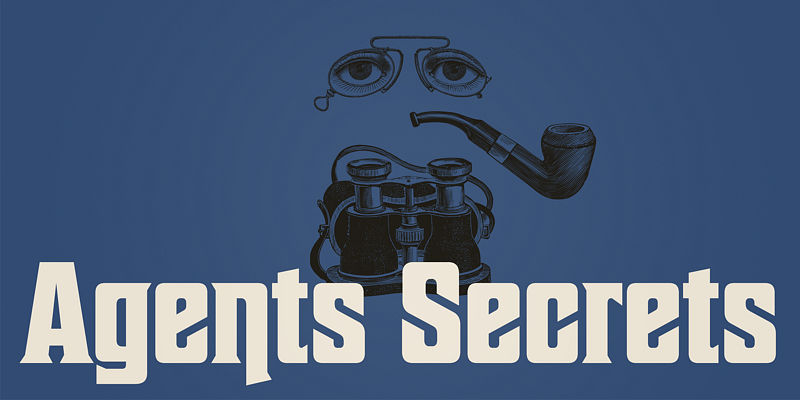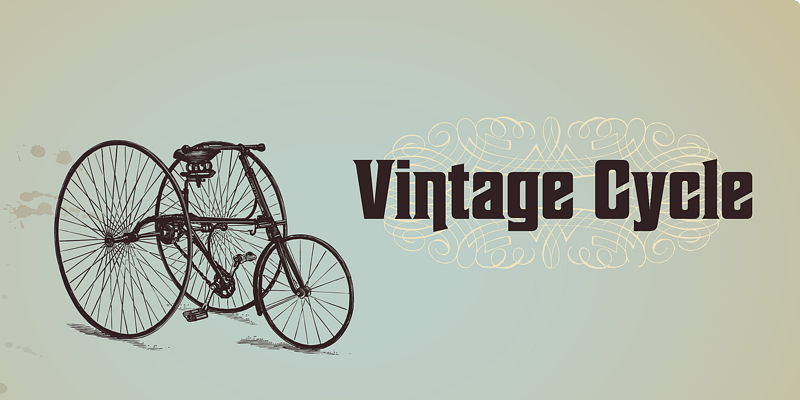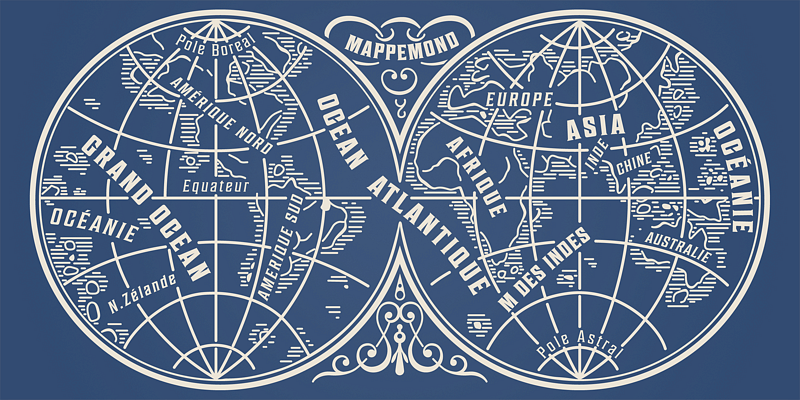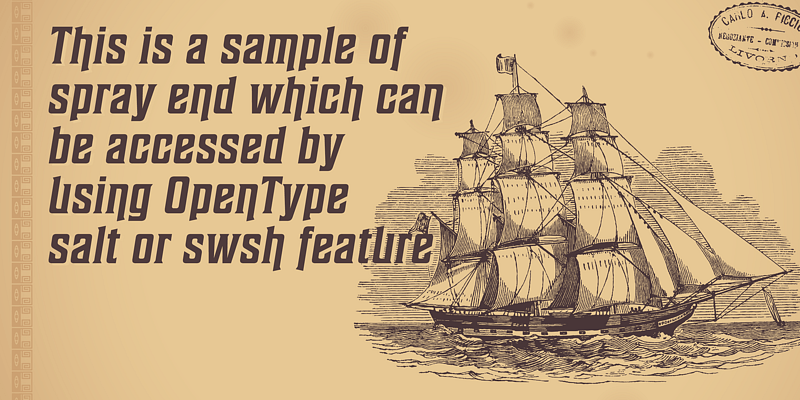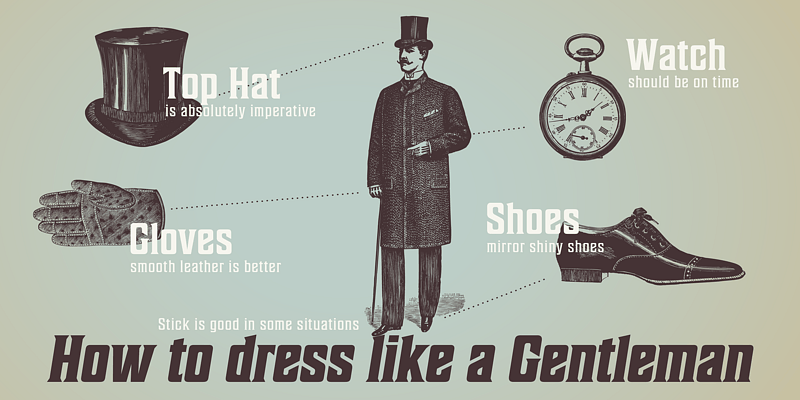
Sheepman a une impression douce et naturelle grâce à son empattement doux et incurvé.
Tous les glyphes ont été conçus avec soin pour avoir l’air rétro de l’ancien temps et pour tout remplir de nostalgie.